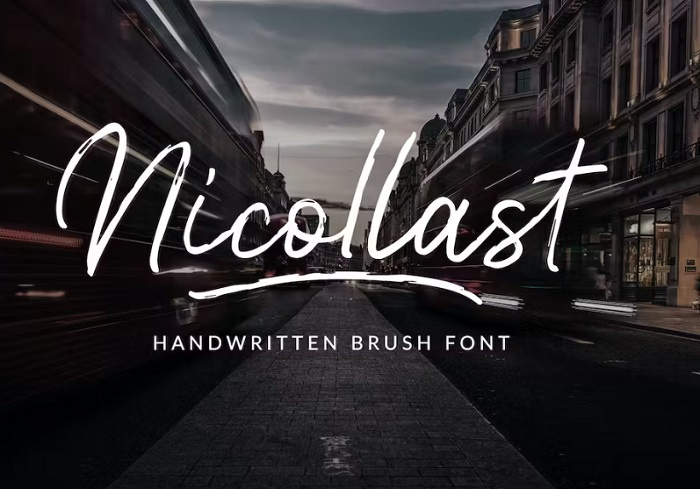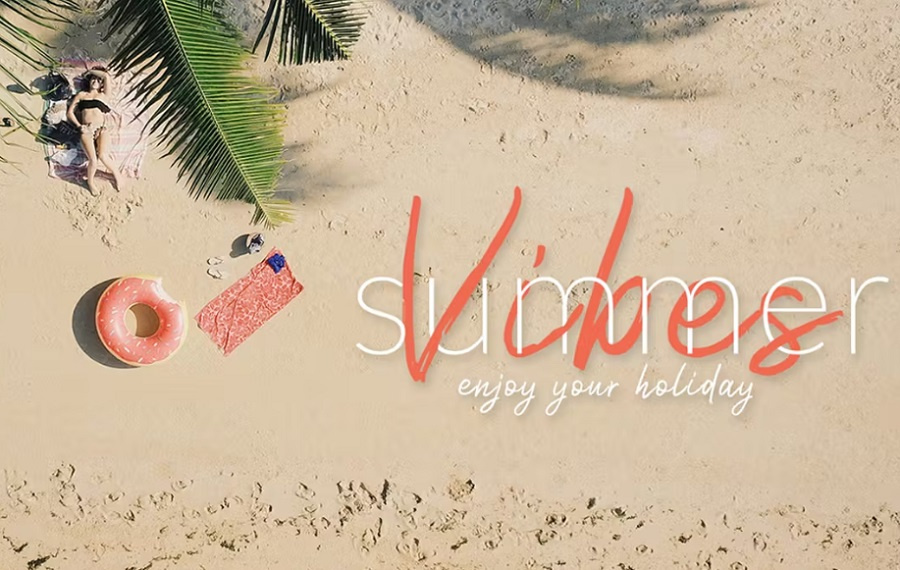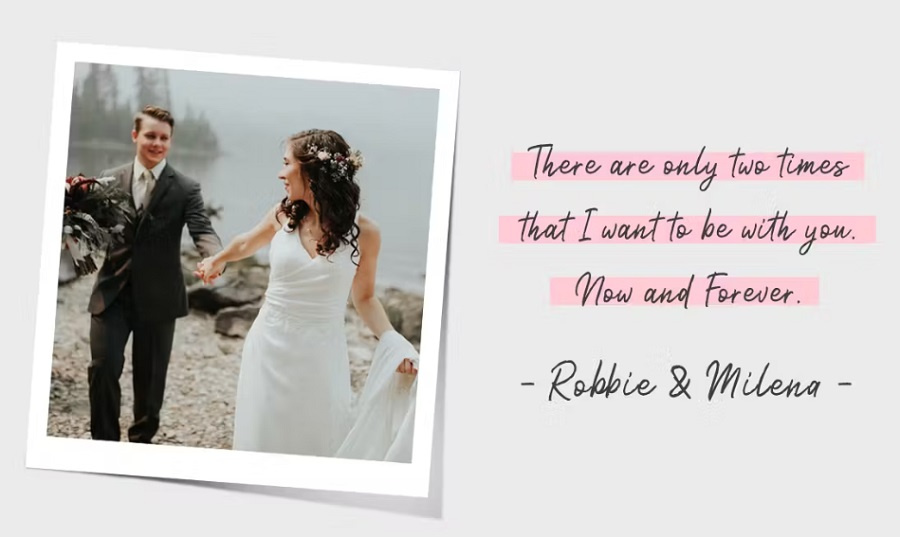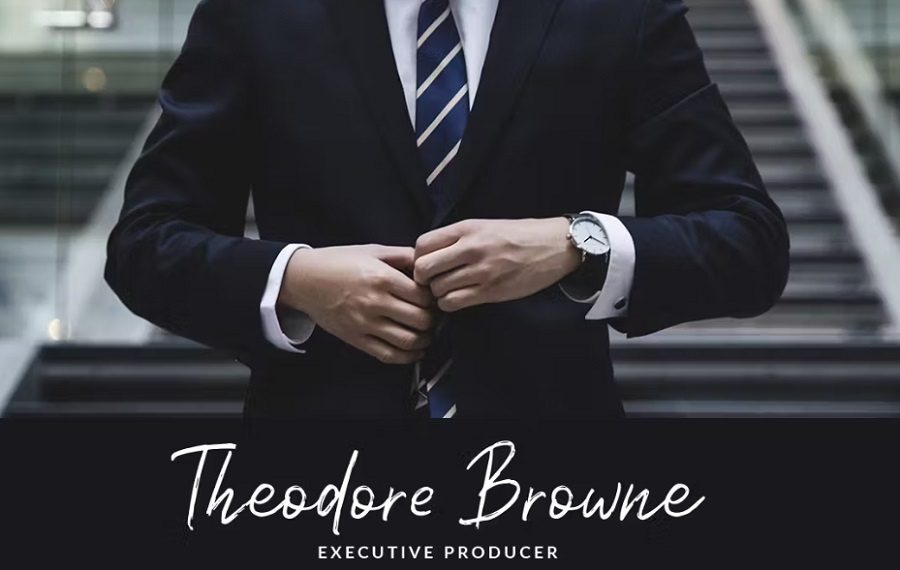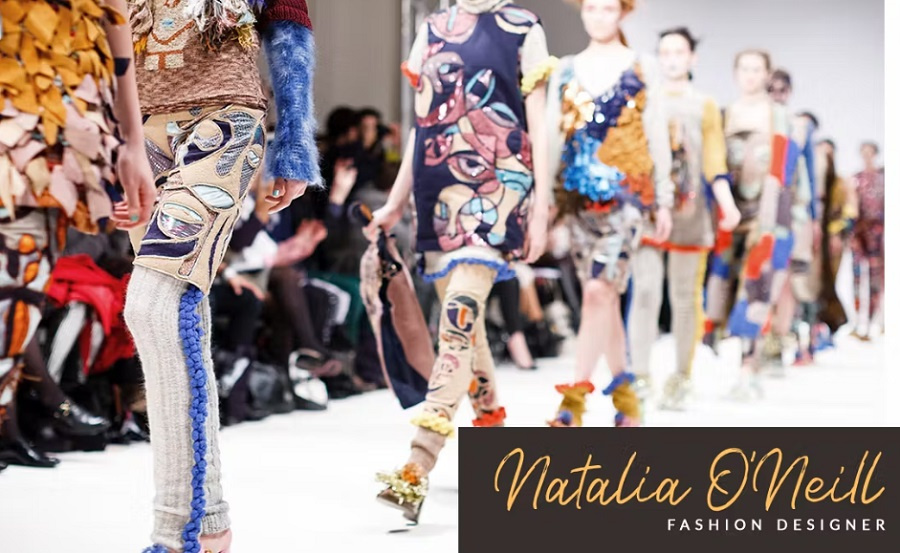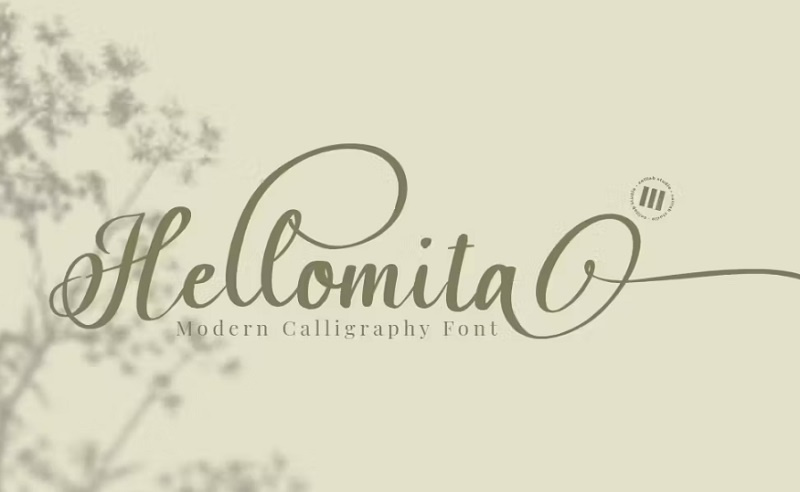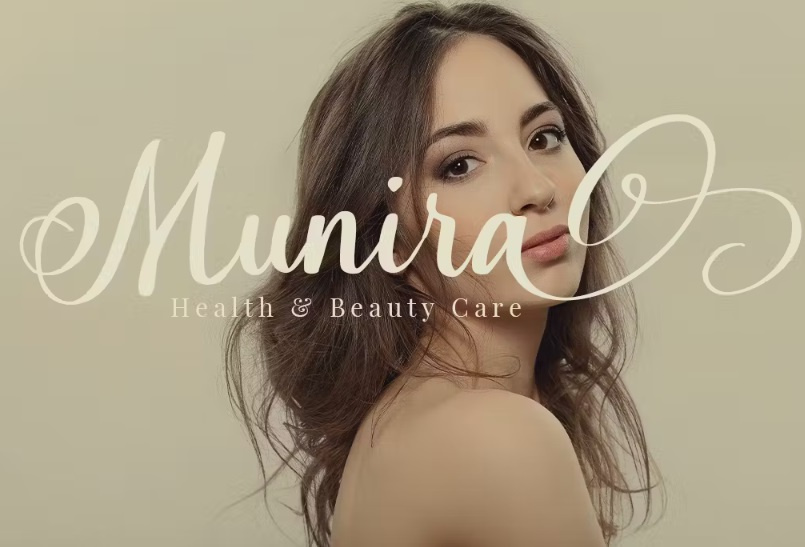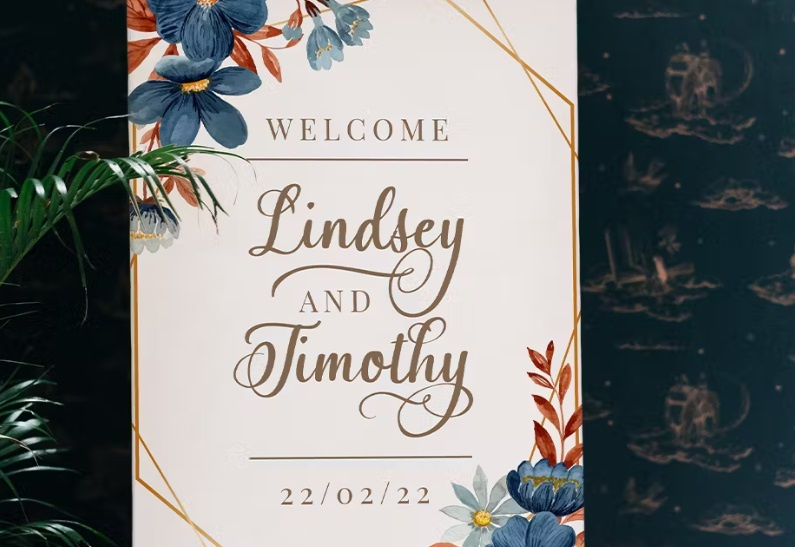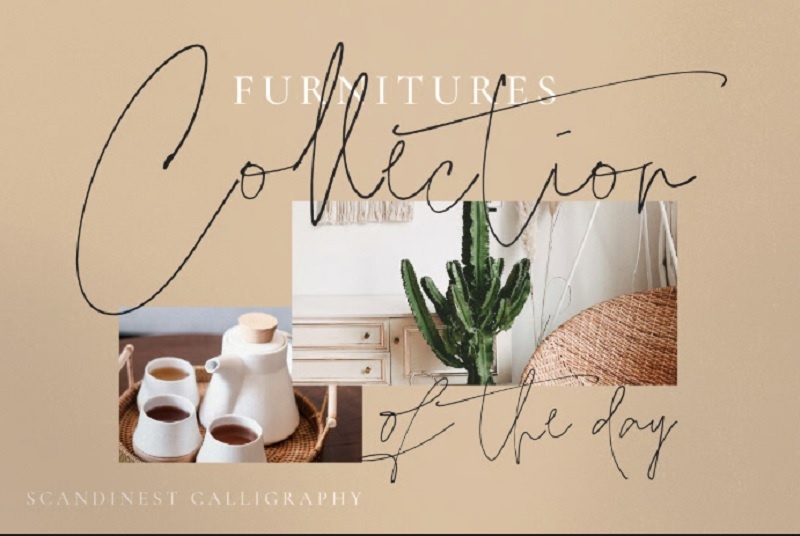
فونت انگلیسی بیو از جی اف ایکس دانلود. در این صفحه با معرفی مجموعه فونت انگلیسی بیو با شما همراه هستیم. این فونت انگلیسی برای بیو عاشقانه، بیو اینستاگرام، تلگرام و ... مناسب است. همچنین می توانید برای امضا، برندسازی، عروسی، مد، عنوان، پوستر، رسانه های اجتماعی، بنر تبلیغاتی، جلد کتاب، بسته بندی، نقل قول های دست نویس، کارت های تبریک و تبلیغات از آنها استفاده نمایید.
Hellomita، یک فونت انگلیسی به سبک خوشنویسی با طراحی مدرن و شیک است. اگر به دنبال فونت انگلیسی برای بیو اینستاگرام خود هستید، این فونت برای پیج شما عالی است. این فونت انگلیسی برای بیوگرافی مناسب برای بیو اینستاگرام، صفحه اصلی وب سایت شما و همچنین سایر پروژه ها از جمله دعوت‌نامه، بسته‌بندی محصول، منوی رستوران و کارت ویزیت و ... نیز است.
✅ نام فونت انگلیسی 1: Nicollast
✅ نام فونت انگلیسی 2: Hellomita
✅ نام فونت انگلیسی 3: Scandinest
✅ تمام فونت های حاوی حروف بزرگ و کوچک، اعداد و طیف وسیعی از علائم نگارشی